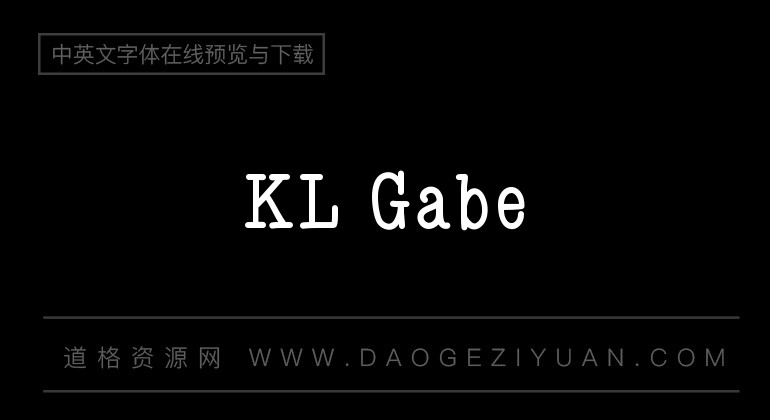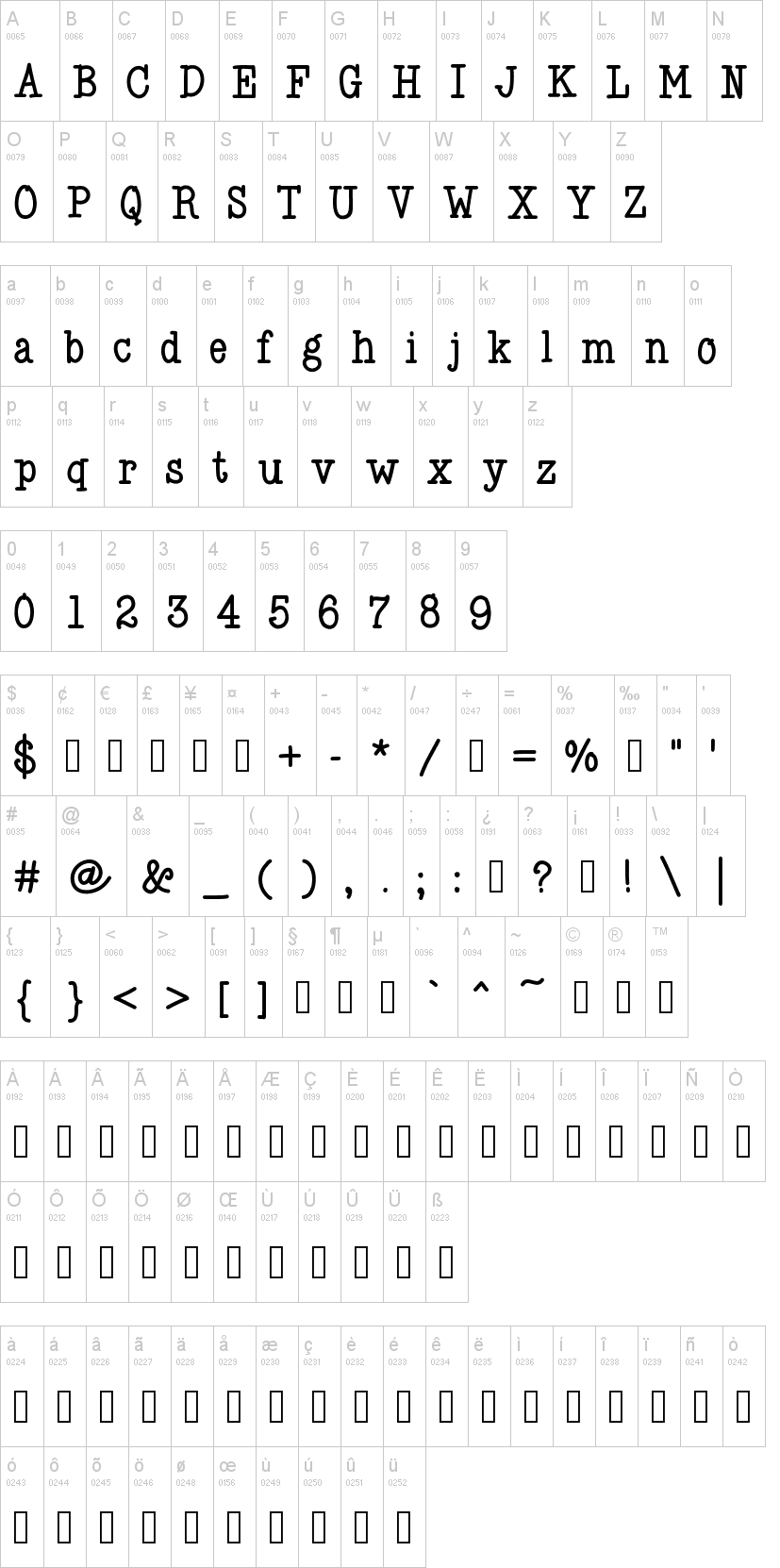
KL Gabe
? KL Gabe 字体是一款由印尼设计师Krisna Londho设计的手写体字体,它独特的设计风格使它看起来有点抽象,但又带有现代感。KL Gabe字体的特点是它的字母和数字都有着曲折的线条,使它看起来有点现代,有点流行。它可以用于标题、标签、报纸、海报等,是一款适合大多数网页设计的字体。
KL Gabe是一款非常不错的手写艺术字体,具有很好的视觉感,适合于文化类的宣传设计、商业类品牌的广告和产品包装设计以及个性化文字排版等较多场景。